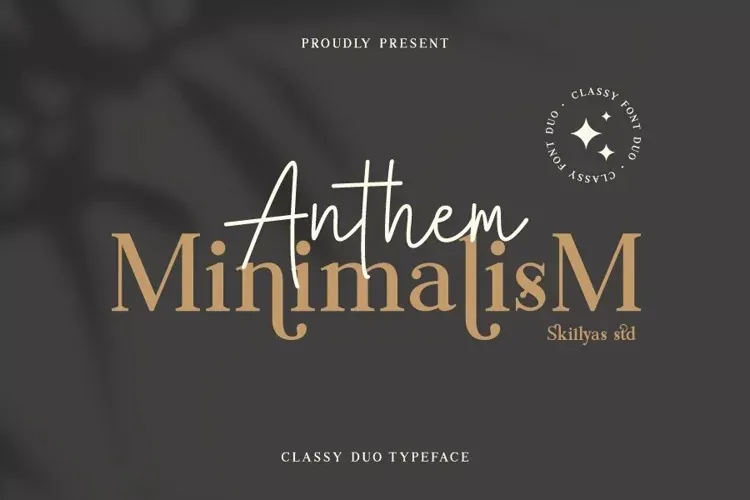
Anthem Minimalism font – Download Grátis
Através do designer 99designs, apresentamos a ‘Anthem Minimalism’ – uma nova opção para os designers que valorizam tanto a elegância quanto a simplicidade. Esta font séria é verdadeiramente única, trazendo um estilo mais moderno e curvas distintas que adicionam um toque especial e glamouroso às suas criações. Ideal para uma variedade de projetos, como fotografia, marca d’água, postagens nas redes sociais, anúncios, logomarcas, convites, design de produto, rótulos, material de papelaria, designs para casamentos e embalagens de produtos. Também se adequa perfeitamente a qualquer projeto que precise dos sutis toques da escrita à mão. A ‘Anthem Minimalism’ é uma font séria que traz unidade e sofisticação ao seu design, sem abrir mão do requinte e originalidade que tanto gosta de incorporar nos seus trabalhos.